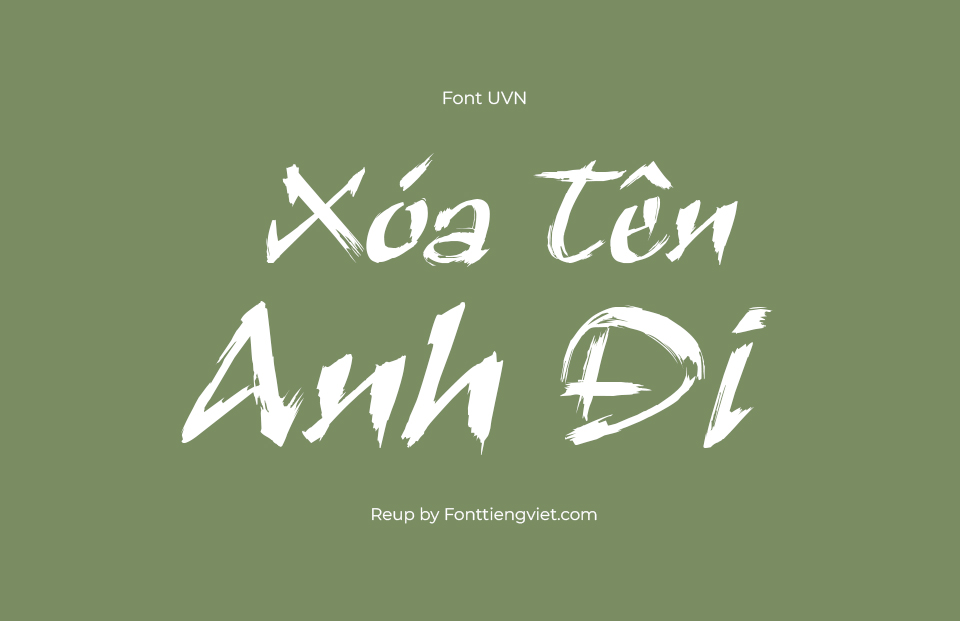
Giới thiệu về Font Việt Hóa UVN But Long 1
Trong thế giới đồ họa hiện đại, việc tìm kiếm một bộ Font Chữ vừa mang nét truyền thống vừa đáp ứng tốt yêu cầu kỹ thuật là điều vô cùng quan trọng. Font Việt Hóa UVN But Long 1 là một trong những đại diện tiêu biểu nhất của bộ mã ký tự Unicode dành cho người Việt. Được thiết kế dựa trên phong cách viết bút lông uyển chuyển, bộ font này không chỉ mang lại vẻ đẹp nghệ thuật mà còn đảm bảo tính tương thích cao trên các phần mềm soạn thảo văn bản và đồ họa phổ biến hiện nay.
Đặc điểm nổi bật của bộ Font Việt Hóa UVN But Long 1
Thiết kế mềm mại và đậm chất nghệ thuật
Đúng như tên gọi, Font Việt Hóa UVN But Long 1 mô phỏng hoàn hảo những đường nét thanh mảnh và dứt khoát của nghệ thuật thư pháp. Các nét chữ được trau chuốt tỉ mỉ, tạo cảm giác như được viết trực tiếp bằng mực tàu trên giấy dó. Điều này giúp bài thiết kế trở nên sinh động và có hồn hơn hẳn so với các font chữ dạng cứng nhắc thông thường.
Tính ứng dụng cao trong môi trường học đường
Với phong cách trang trọng nhưng không kém phần gần gũi, bộ font này cực kỳ phù hợp cho các em học sinh và thầy cô giáo. Bạn có thể sử dụng Font Việt Hóa UVN But Long 1 để làm tiêu đề bài giảng, thiết kế thiệp mời họp phụ huynh, hoặc trang trí các bảng tin lớp học. Sự rõ ràng của bộ chữ giúp người xem dễ dàng tiếp nhận thông tin mà vẫn cảm thấy sự tinh tế trong từng nét chữ.